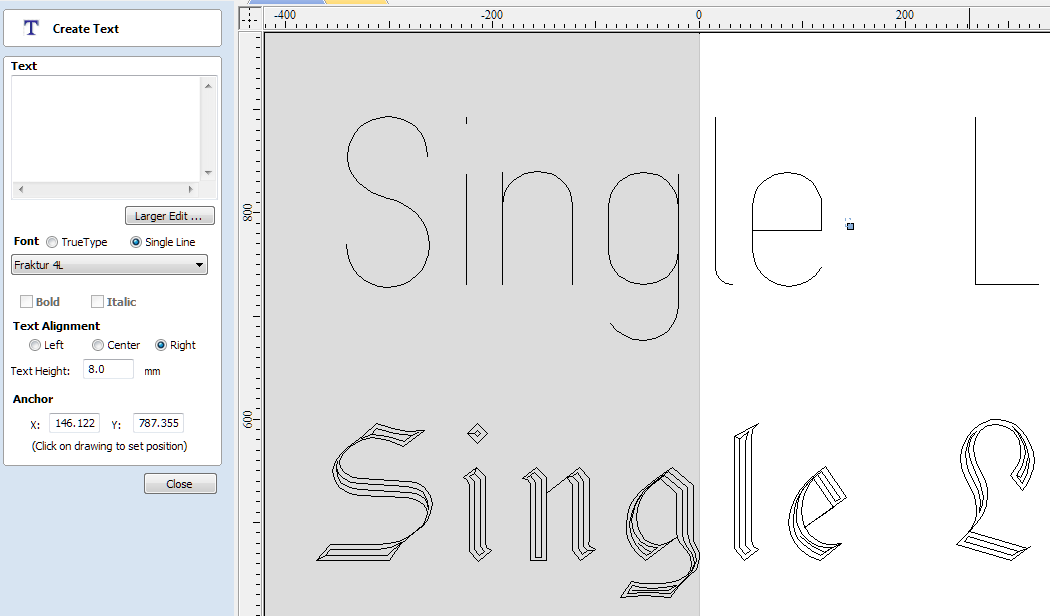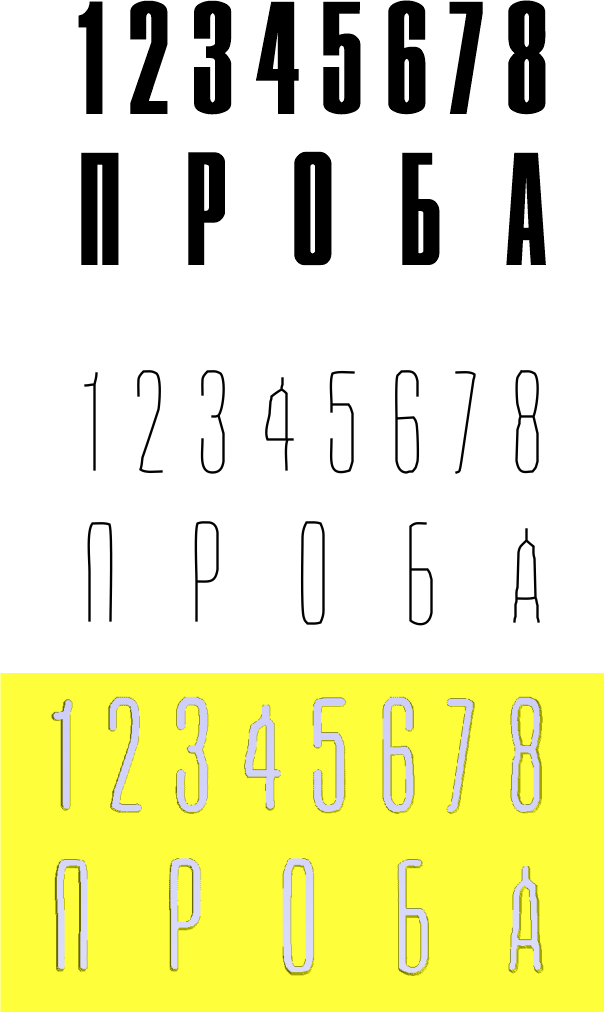
Как назвать шрифт, все элементы символов которого имеют одинаковую ширину?
Без зачечек, конденсед. И хвосты, и наплывы, и полуовалы.
Элементы это штрихи?
Геометрический гротеск наверное, неконтрастный
Все должно быть по ширине основного штриха.
Centerline?
Vectric Aspire называет такие single line. Но там они реально Single line, просто линией нарисованы, а толщина появляется только при фрезеровки и зависит от формы фрезы. Вероятно, вопрос о других, но, тем не менее...
Интересный подход. Мне надо именно для фрезеровки. Вот как переварит такие линии GGEasy...
Хотя я могу задать желаемую толщину абрисом и перевести его в объект. Надо пробовать.
Там используются свои шрифты, специально нарисованные. Сколько было обсуждений этих "монолинейных" шрифтов, русских никто не сделал. Я либо использую в таких случаях латинские буквы, где можно заменить, либо рисую векторами. Получить специфический шрифт кажется довольно сложной задачей.
Вот так нормального качества шрифт сделать не получится. Тогда уж лучше V-Carve использовать.
Он будет строго по краям буквы делать, хотя глубина может варьироваться, особенно при использовании граверов или угловых фрез.
Из плюсов - скорость гравировки, то есть он, зачастую, и будет гравировать одним проходом, в зависимости от инструмента и шрифта, естественно. Ну и Flat Depth'а
Кстати, вот и русское название вспомнил выше - "монолинейные". Их много обсуждали, толку 0
Увидел в сообщениии ~RA~ термин "centerline" и подумал, что можно отрастрировать надпись, а потом отвекторизовать в режиме "centerline". Попробовал, шляпа, конечно, но можно попробовать доработать, а потом гравировать по линии.
Вот образец "на автомате", с имитацией в Aspire. Так себе, конечно. Опять же, сильно зависит от размера надписи и диаметра/формы фрезы/гравера
Для какой программы? Винда такие не умеет, автокадовские shp/shx только там и работают, от Aspire тоже только в нем читаются